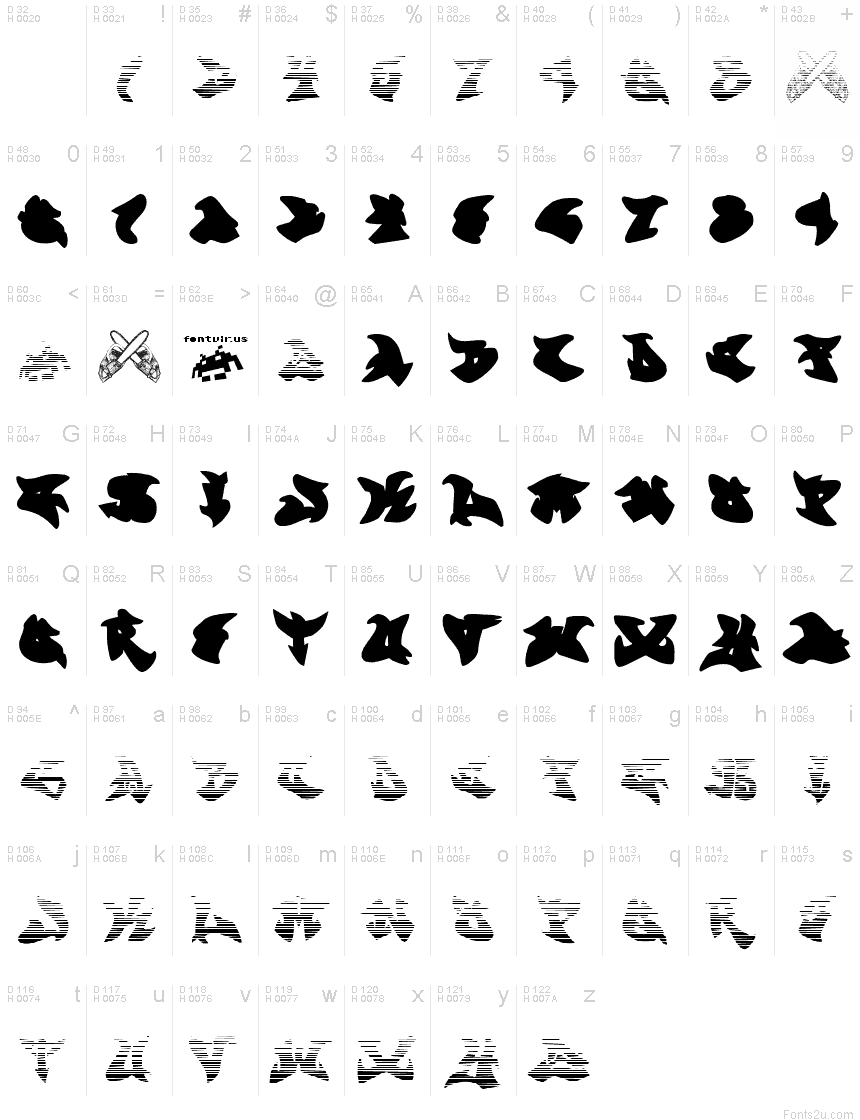
Graffonti Gradient Fill от Xero Harrison — это бесплатный граффити-шрифт с дерзким уличным характером. Буквы пропитаны энергией вайлдстайла: острые углы, вытянутые диагонали и горизонтальные полосы создают эффект напыления через трафарет.
Отлично подходит для заголовков плакатов, обложек микстейпов, скейт-графики, названий зинов и клубных флаеров, где нужен бесплатный шрифт с характером посильнее, чем у обычного тег-скрипта. Благодаря полосам, которые агрессивно прорезают каждую букву, этот шрифт идеален для коротких заголовков, логотипов и монограмм, где главную роль играет текстурная заливка.